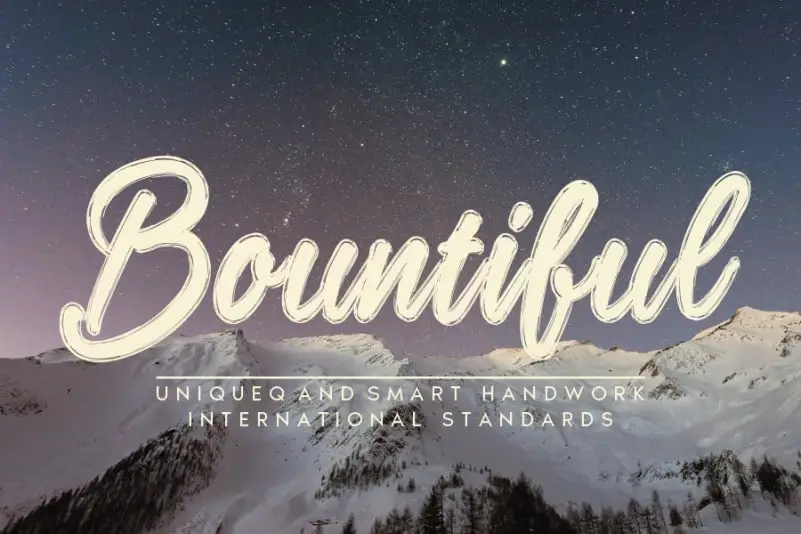
Bountiful Script Font – Download Grátis
A Bountiful Script Font é uma elegante adição à categoria dos fontes script para designers do Brasil. Inspirada na tipografia clássica, ela traz sua própria estética única aos projetos de design. Este belo tipo feito a mão se destaca como o perfeito complemento para headlines em qualquer tamanho, bem como blocos de texto que possuem variações tanto de máxima quanto mínima. Com seu design sofisticado e caracterizado por suas linhas arredondadas e texturas suaves, a Bountiful Script Font é uma escolha ideal não apenas para aplicação web ou impressão, mas também para vídeos em movimento. Seja no seu website empresarial, livro de capa ou qualquer outro projeto gráfico, a Bountiful vai brilhar como protagonista. Esta fonte criada pelo designer andikastudio é perfeita para quem busca uma opção diferenciada e sofisticada para suas criações graficas. Ela enriquece os seus projetos com um toque especial que faz toda a diferença no resultado final, sejam eles em formato impresso ou digital.